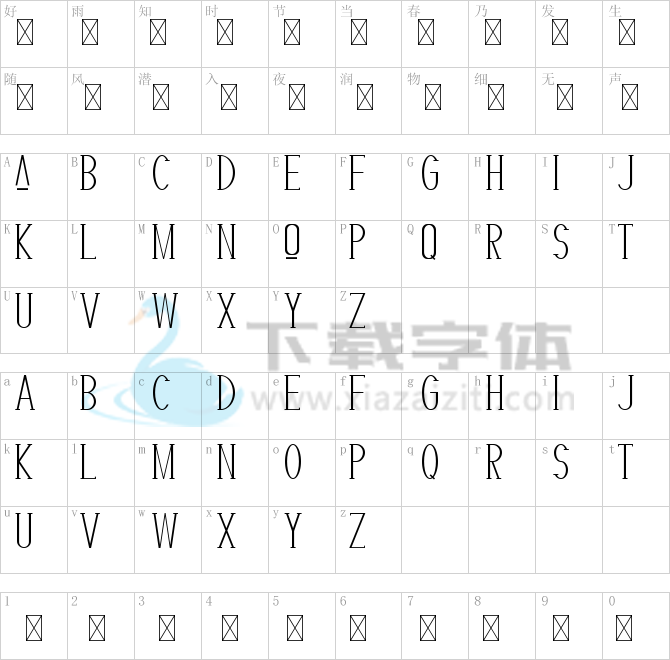
Authoria Demo.ttf字体下载,这款字体结构工整、笔画清晰,兼顾美观与易读性,适用于标题、正文、海报、包装、LOGO 等多种场景。字形优雅稳定,风格百搭耐看,适配日常排版与创意设计,让文字呈现更舒适、更具质感。Authoria Demo.ttf字体下载一笔一画,皆是细节,以均衡的比例、流畅的线条打造舒适视觉体验,字形端正大气,风格简约现代。无论是商业设计、品牌宣传还是日常排版,都能轻松驾驭,让文字更有格调与力量。Authoria Demo.ttf字体下载字体下载。